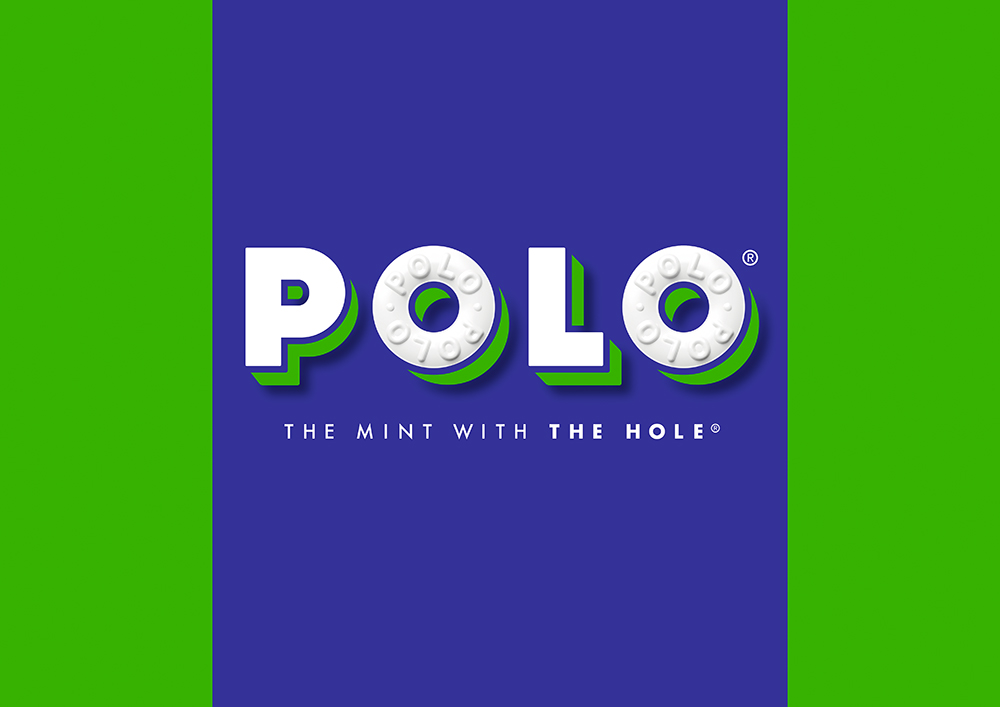
상쾌함이 폴~폴~, 폴로 리브랜딩 스토리
폴~폴~, 폴로 리브랜딩 스토리
폴로는 영국의 대표 민트 제품이란 지위를 굳건히 하고자 브리스톨의 에이전시 택시에게 리브랜딩을 의뢰했다. 택시는 매대 위에서도 돋보이고 젊은 소비자에게도 호소력 있는 디자인을 위해 흰색을 활용하여 모던하고 깔끔한 브랜드 마크를 제작했다.
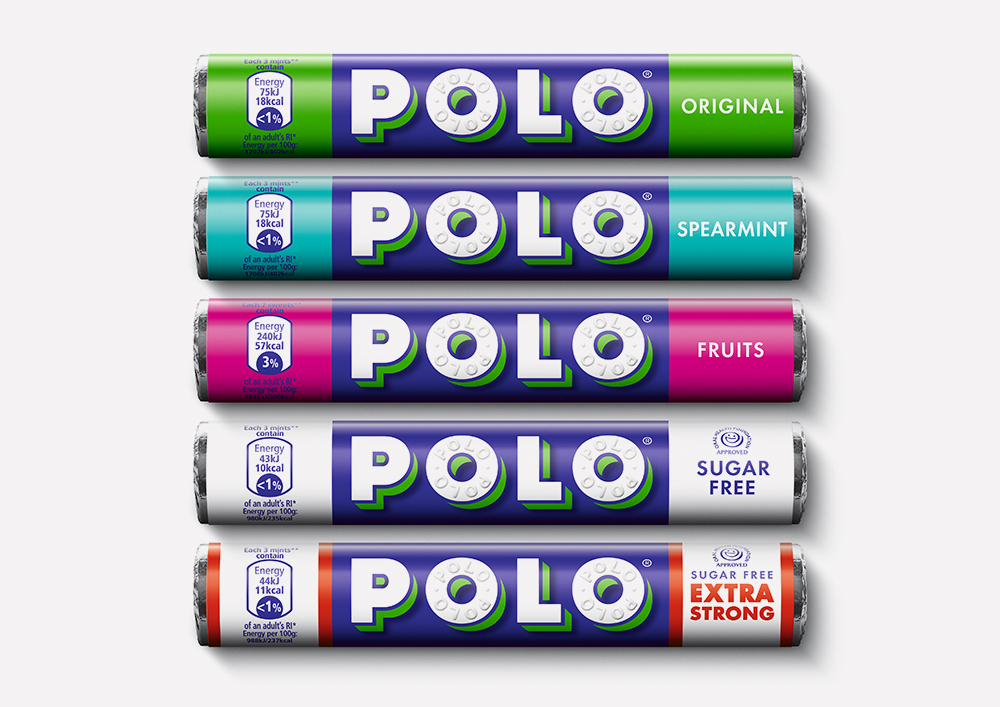
“친숙함을 잃지 않는 데에 주력했습니다. 새로운 모습으로 재탄생하더라도 사람들은 여전히 폴로를 ‘나의 폴로(my POLO)’로 인식해야 하니까요.” 크리에이티브 파트너이자 공동 설립자인 스펜서 벅(Spencer Buck)이 말한다.
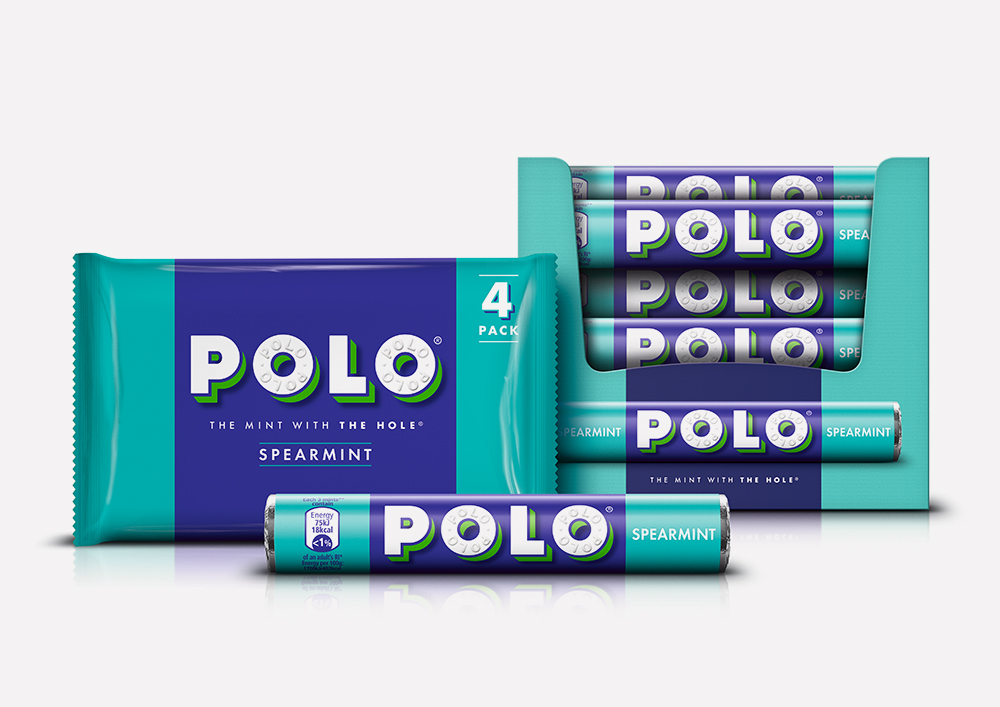
“제일 어려웠던 점은 리브랜딩을 적용할 포맷이 협소했다는 겁니다.” 스펜서는 이 작업에서 가장 주의를 기울인 부분은 브랜드 마크를 흰색만으로 제작하는 것이었다고 덧붙인다.
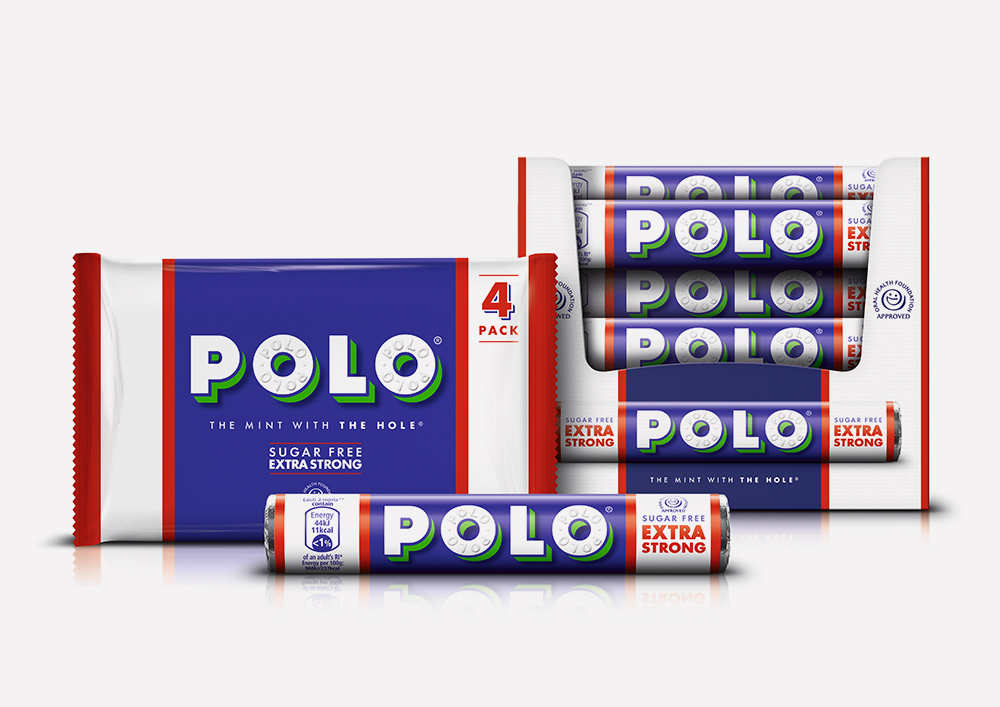
“폴로 브랜드 역사상 이전에는 이런 예가 없었으며, 특히 패키지의 경우에는 전무합니다. 폴로의 전통을 존중하는 것이 리브랜딩 계획의 최우선 조건이었습니다. 그리고 우리는 그것을 해냈죠.”